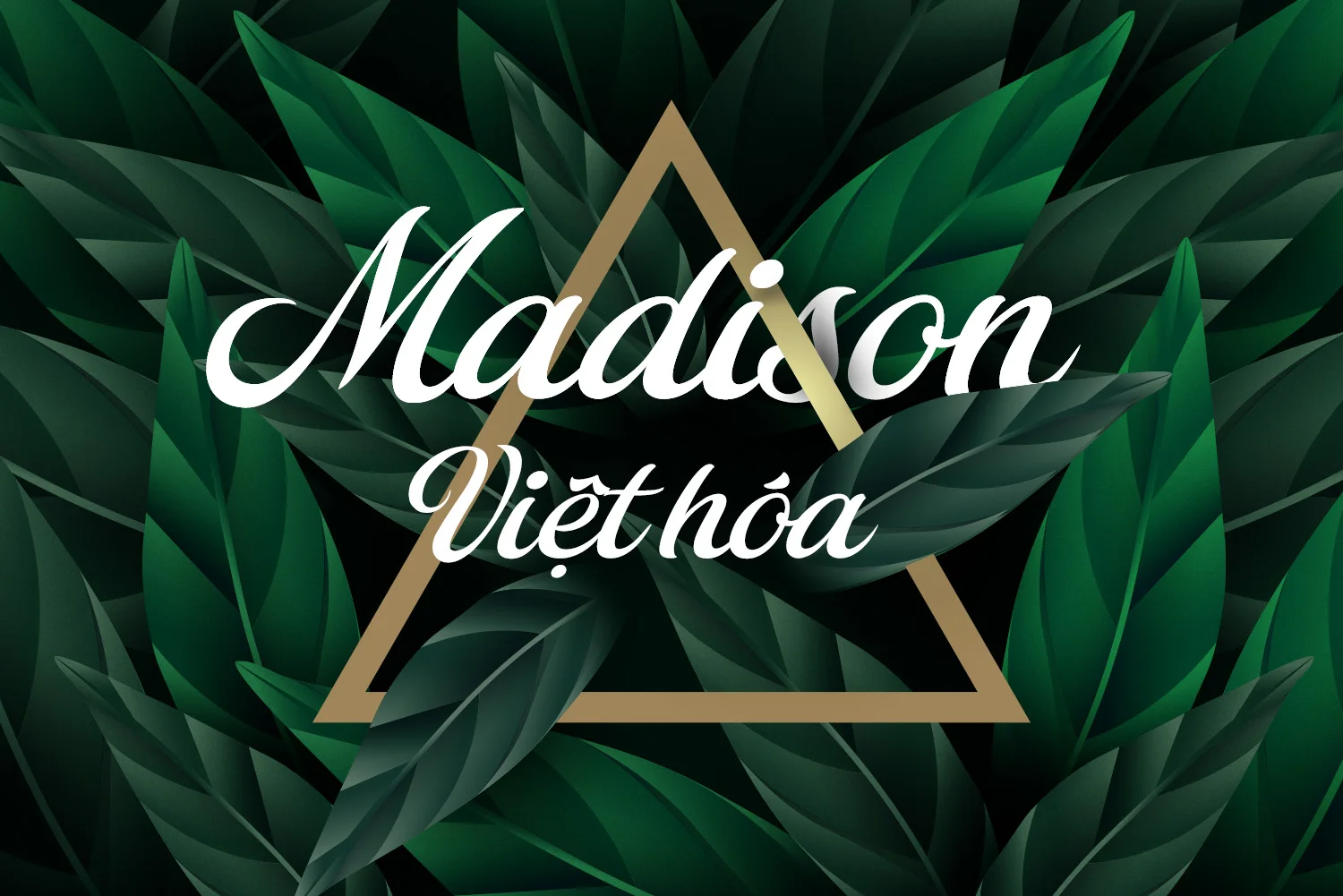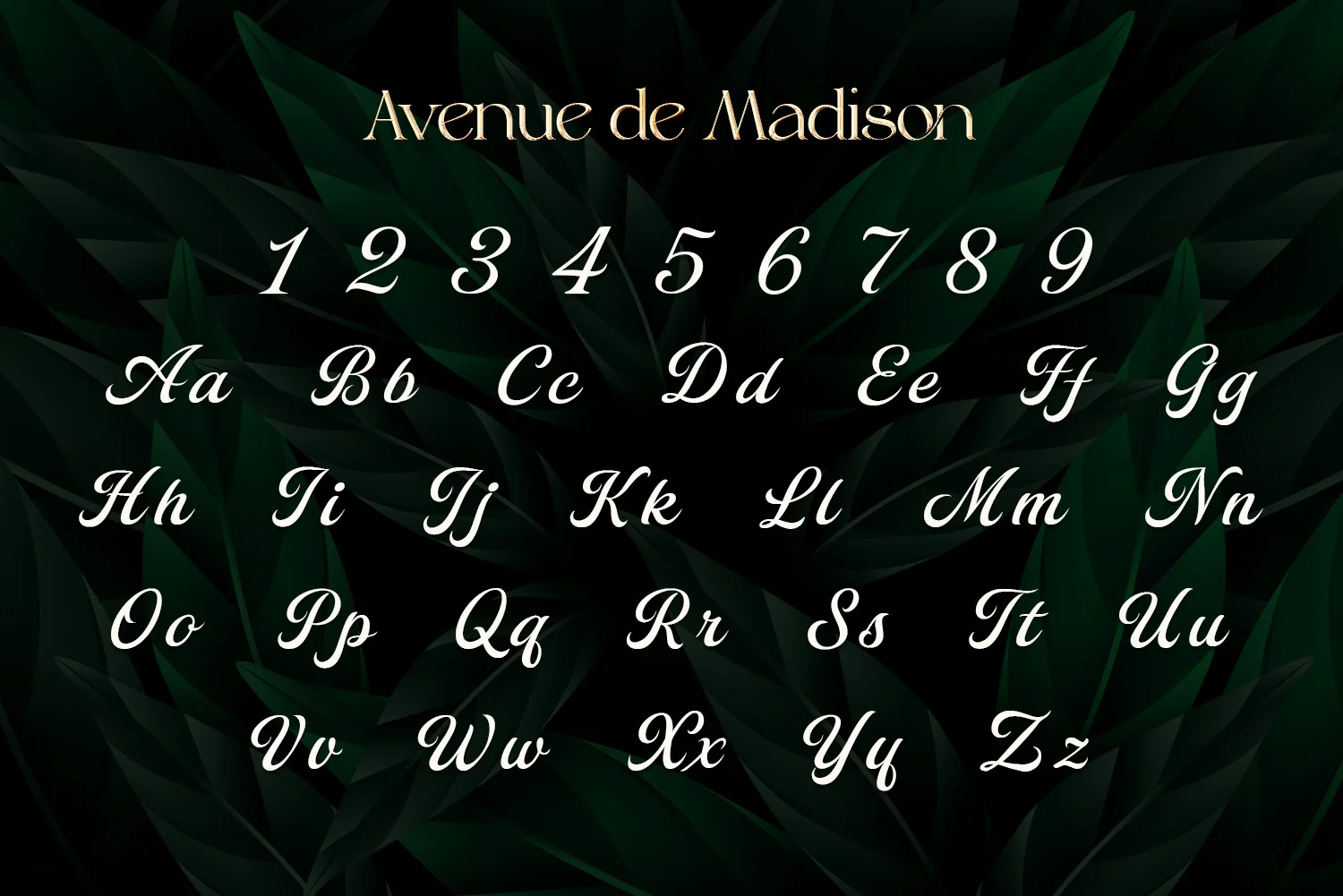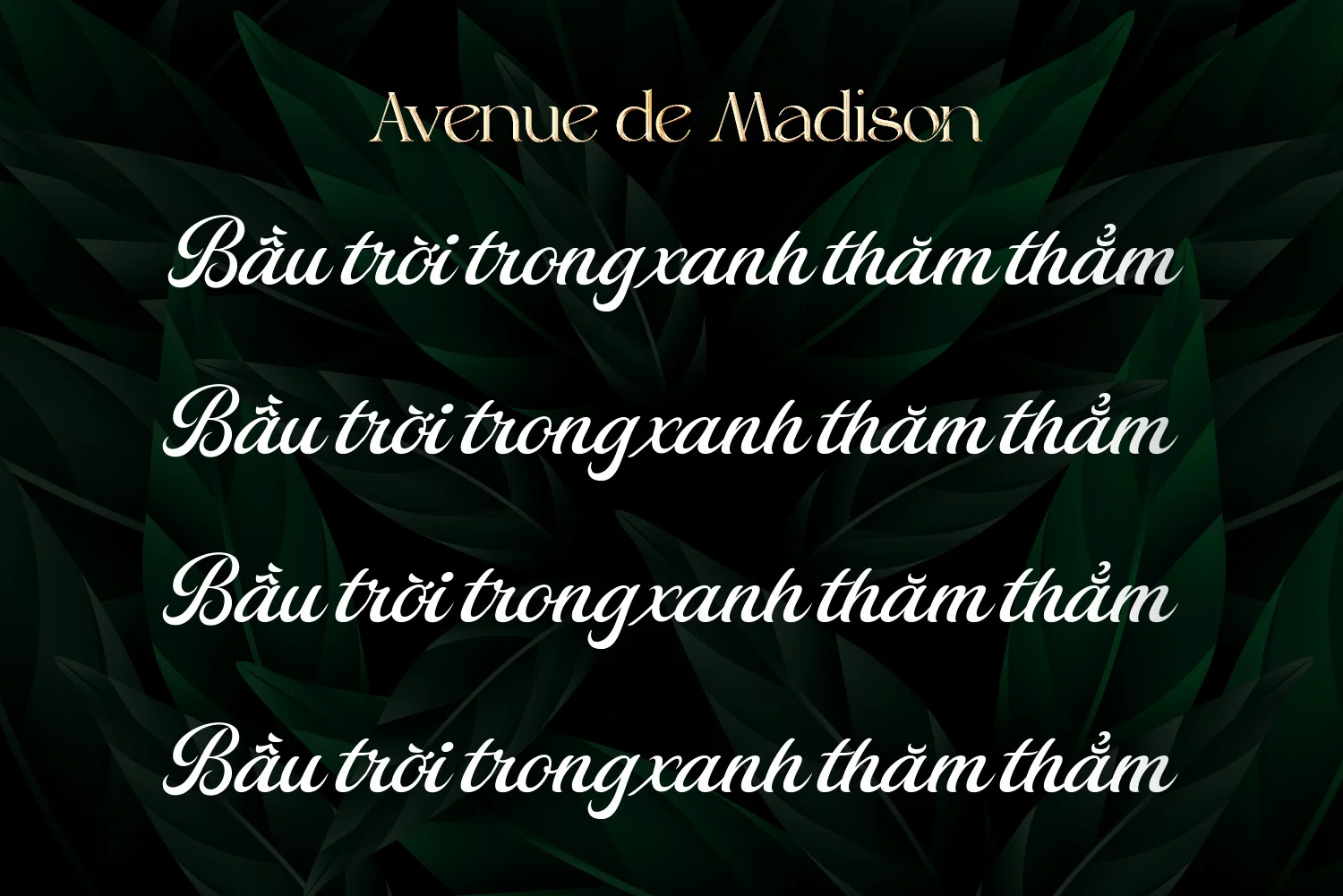
DVN Avenue de Madison Việt hóa là một font chữ viết tay mềm mại, mang đậm cảm xúc và sự tự nhiên trong từng đường nét. Các ký tự được thiết kế tinh tế, có độ nghiêng nhẹ và chuyển động nhịp nhàng như được viết bằng bút mực trên giấy. Phù hợp với nhiều thể loại thiết kế như nhật ký, thiệp, thơ, blog cá nhân, hoặc những dự án sáng tạo đòi hỏi yếu tố nhẹ nhàng, gần gũi và giàu tính biểu cảm. Bộ font gồm đầy đủ chữ hoa, chữ thường và đã được Việt hóa đầy đủ dấu tiếng Việt, giúp bạn sử dụng linh hoạt trong thiết kế ngôn ngữ bản địa. DVN Avenue de Madison là lựa chọn lý tưởng để truyền tải thông điệp bằng chữ viết tay, mang lại cảm giác chân thật và sâu lắng cho người xem.